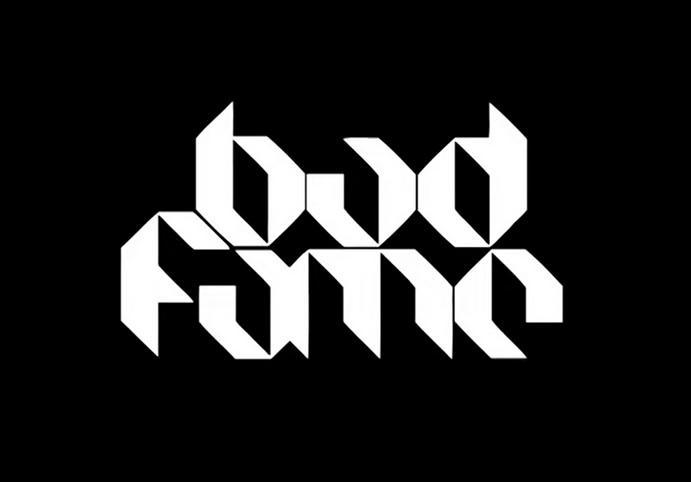
Geometrischer, zweidimensionaler, sehr flächiger Font
heute bin ich in einem etwa 12 Jahre alten mexikanischen Rapvideo auf ein Intro gestossen, das den Schriftzug von BadFame Productions zeigt. Ich habe mich gefragt, ob dieser Font ein Eigenbau ist oder ob es diesen tatsächlich gibt, da ich für ein Shirtdesign genau so eine plakative Schrift suche. Leider habe ich nichts weiter von diesem "Unternehmen" gefunden. Ich würde mich freuen, wenn irgendwer diese Schrift erkennt oder mir eine Alternative nennen kann.
Ich hatte es mit "what the font" probiert, allerdings ohne ordentliche Ergebnisse.